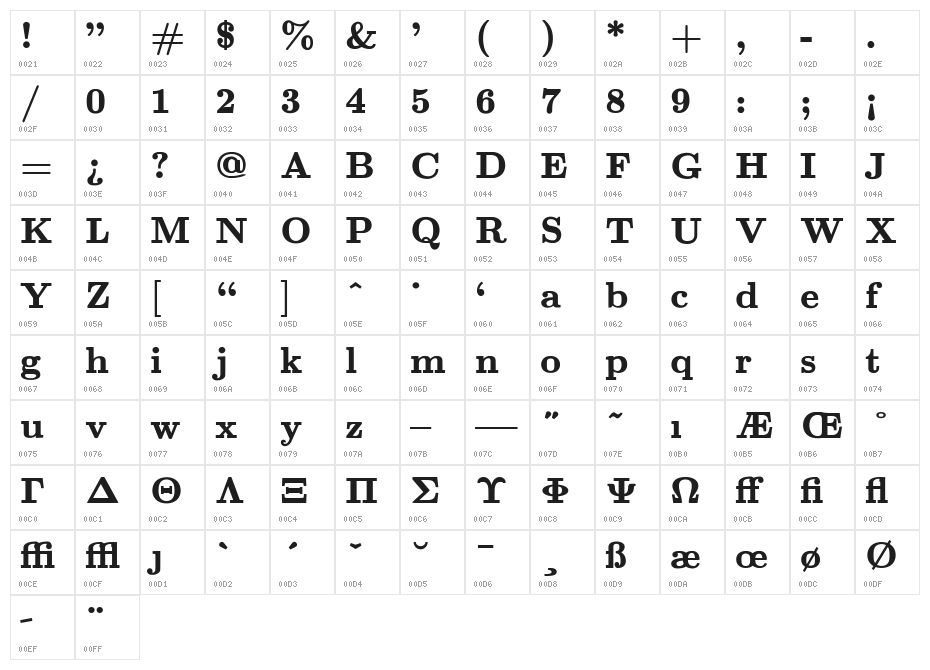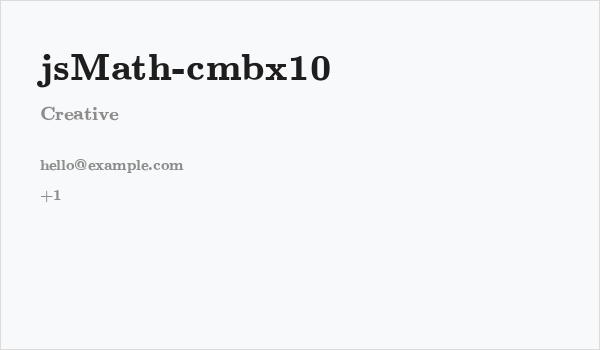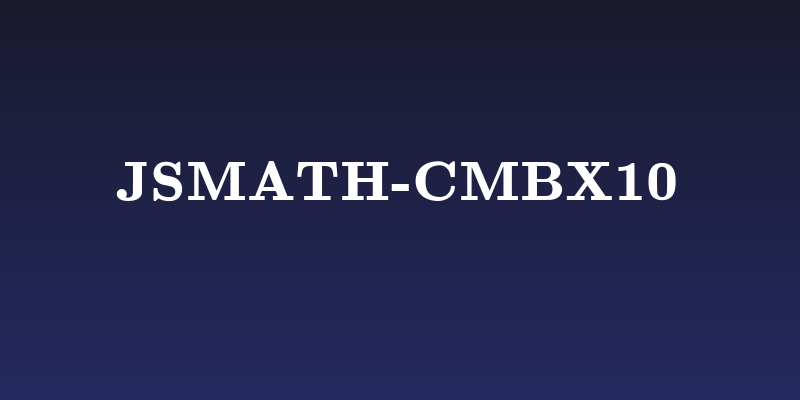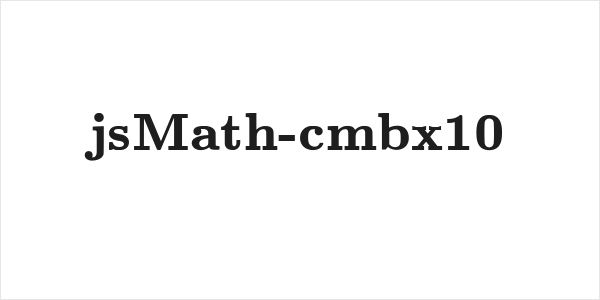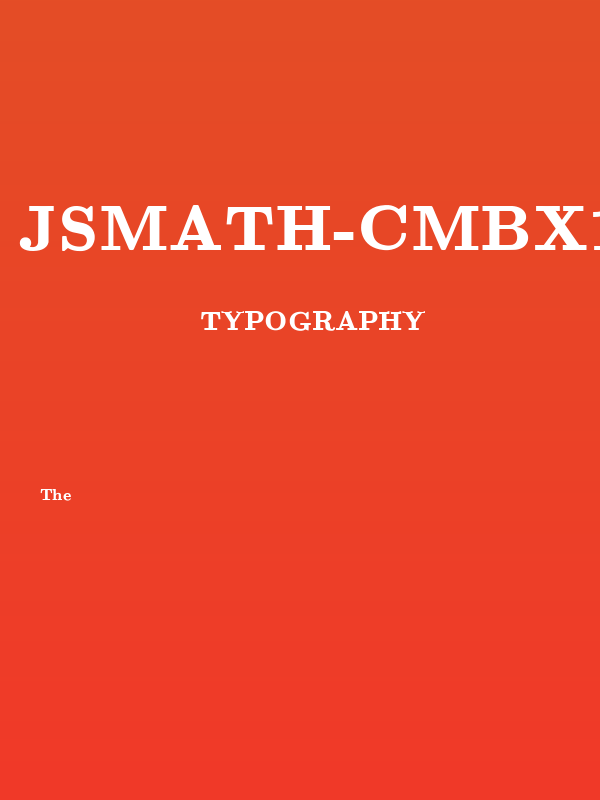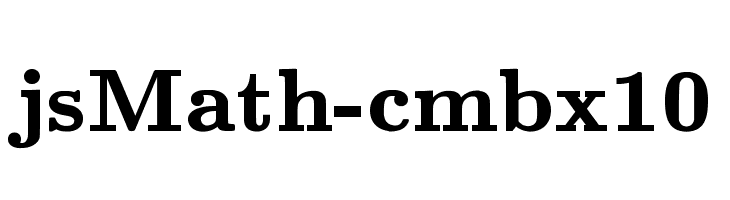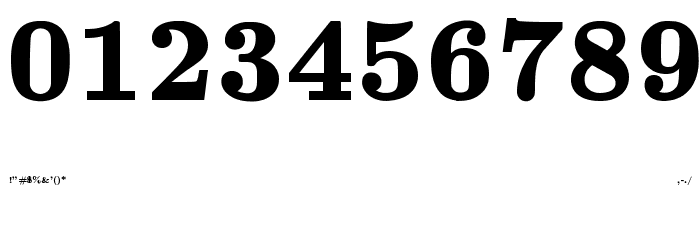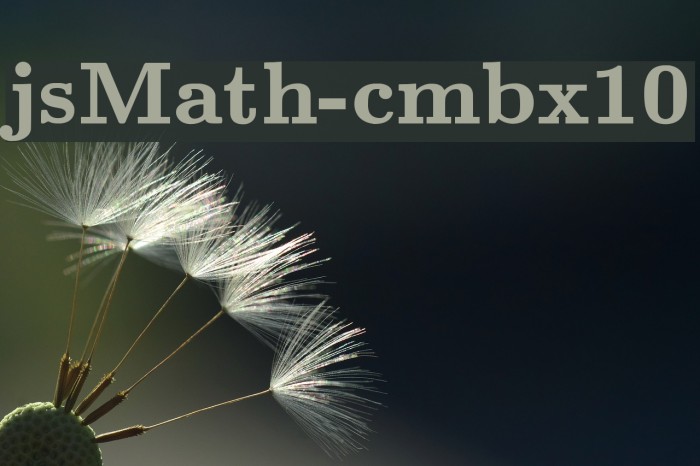
jsMath-cmbx10 Font
| おすすめプロジェクト | Ideal for use in formal documents, book titles, editorial design, and branding that requires a traditional and authoritative look. |